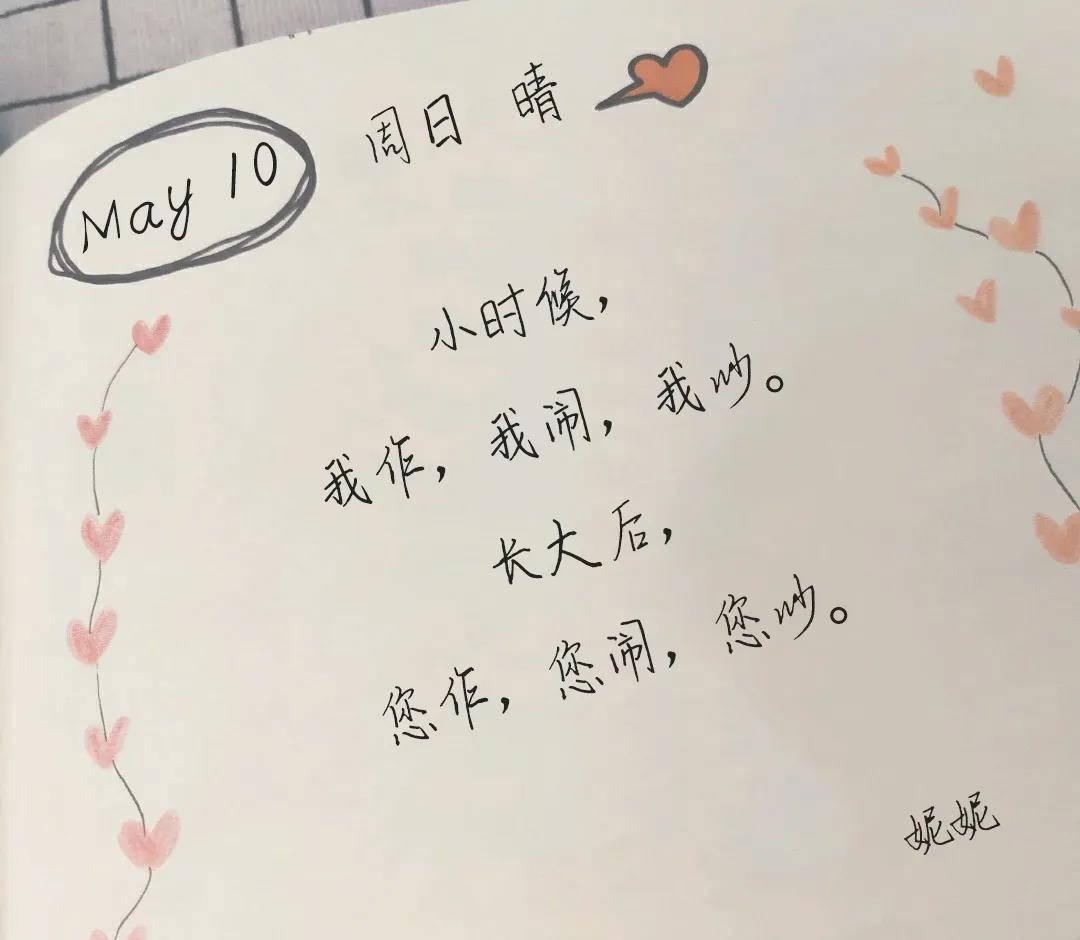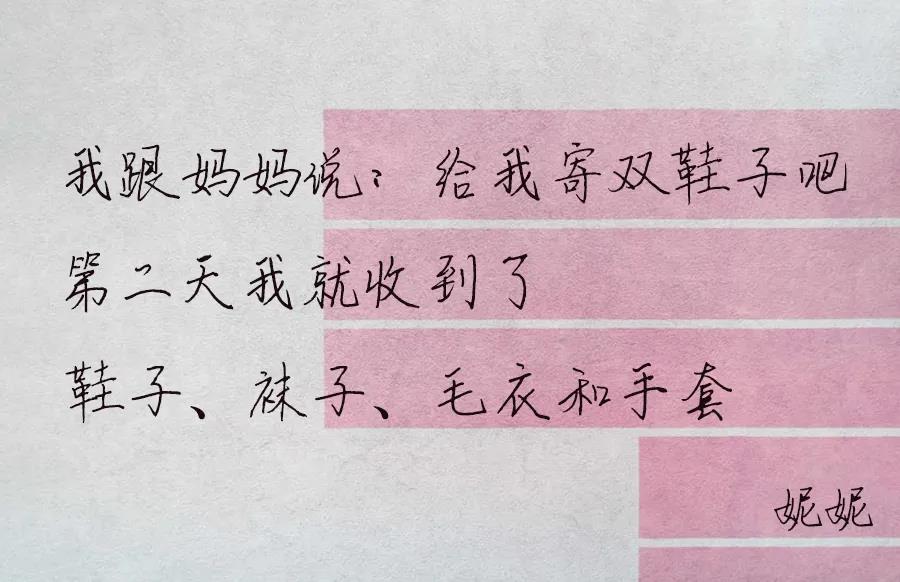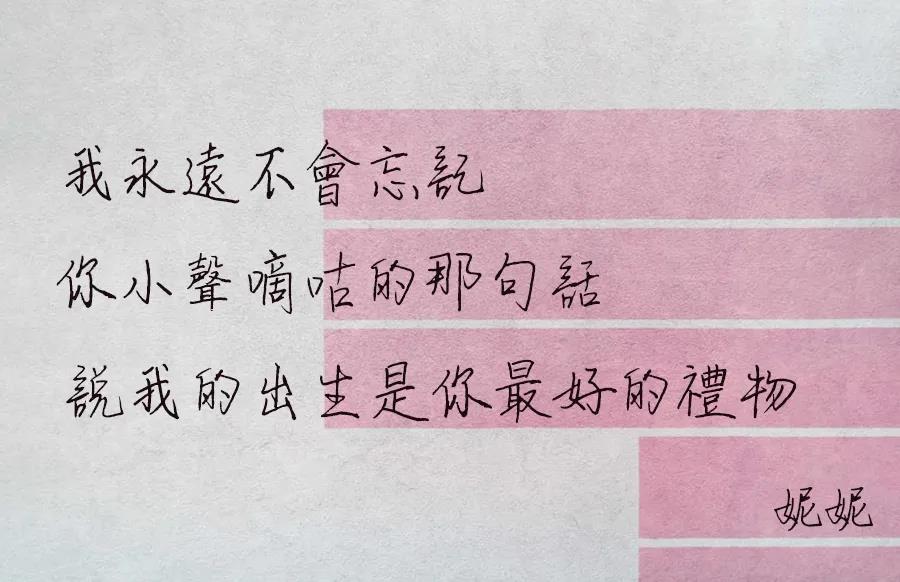
騰祥妮妮手跡字體書寫連貫輕松自如,平實(shí)無華的風(fēng)格透顯出質(zhì)樸與生機(jī),充滿活力。適用于正文更體現(xiàn)出親切、自然之感,具實(shí)用性。本作品可適用于屏幕顯示、印刷出版、包裝設(shè)計、廣告設(shè)計、網(wǎng)頁設(shè)計等。
簡/繁效果展示